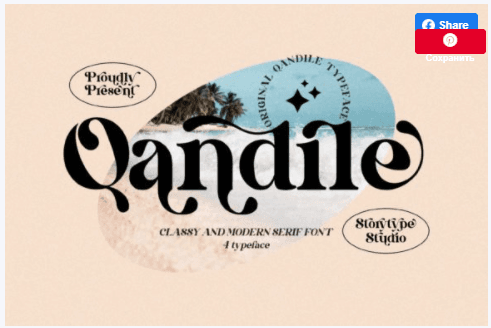
Qandile Font
Qandile - это напористый и отличный шрифт с засечками. Он закодирован в формате PUA, что означает, что вы можете легко получить доступ ко всем глифам и росчеркам! Добавляйте Qandile уверенно к своим любимым творениям и позвольте себе поразиться полученному результату.